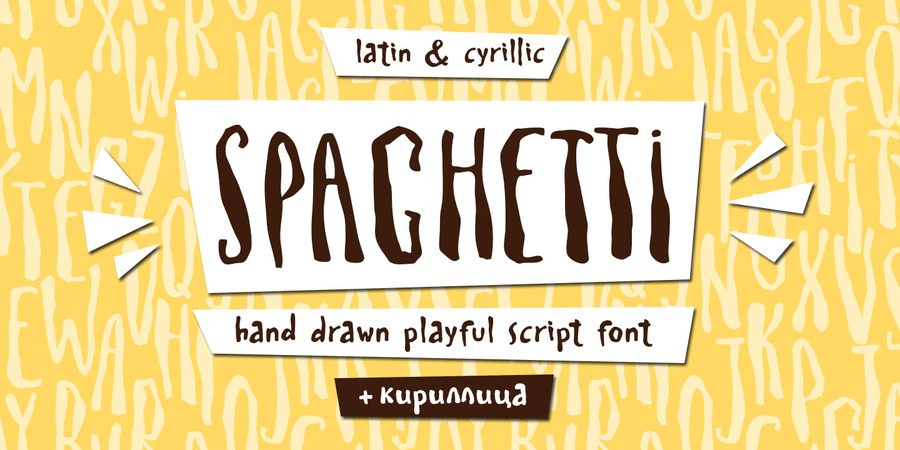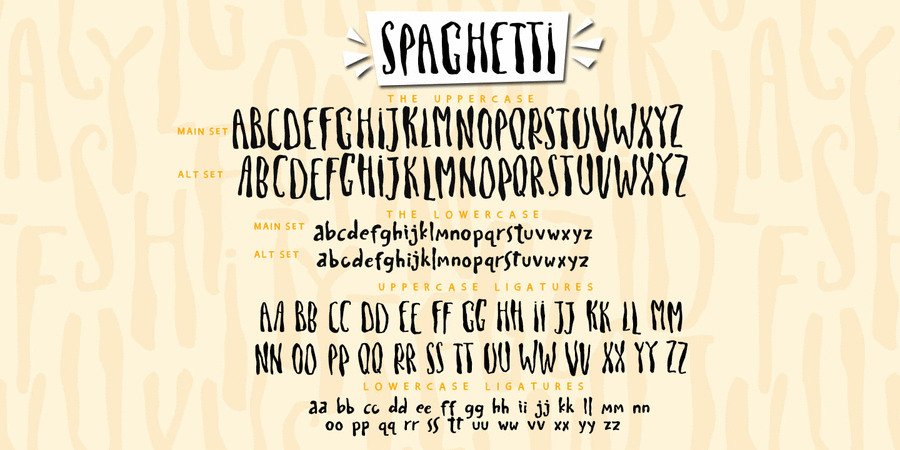
Грайливий симпатичний шрифт Spaghetti включає в себе основний і альтернативний набір великих букв, основний і альтернативний набір малих букв, а також повний набір подвійних букв у верхньому і нижньому регістрі, а також великий діапазон цифр і розділових знаків. Шрифт Spaghetti ідеально підходить для використання у всіх ваших кумедних дизайнерських проектах, будь то логотипи, етикетки, дизайн упаковки, заголовки блогів. Крім того, він буде мати гарний вигляд на листівках, заголовках дитячих книг та інших друкарських проектах. Spaghetti Symbols – це додатковий шрифт з 52 намальованими від руки картинками, цельнімі словами, стрілками і розчерками, який допоможе зробити ваш дизайн більш оригінальним. Комбінуйте елементи та ілюстрації, щоб створювати свої власні дизайни, рамки, роздільники, логотипи та багато іншого (просто за допомогою клавіш A-Z і a-z в доданому шрифті Spaghetti Symbols). Кожному стандартному символу верхнього або нижнього регістру призначається інший символ, тому вам не потрібно графічне програмне забезпечення, просто введіть потрібну літеру. Включена велика мовна підтримка: Мови Західної Європи, Центральної і Південно-Східної Європи, а також кирилиця. ОСОБЛИВОСТІ ШРИФТУ: контекстні альтернативи для більш природного рукописного тексту в програмах з можливістю Opentype, 52 лігатури з подвійних букв для більш індивідуального вигляду, додаткові стилістичні альтернативи для всіх символів. Кодування PUA: доступ до додаткових гліфів можна отримати через карту символів або книгу шрифтів (можна копіювати і вставляти потрібні гліфи, коли панелі Opentype недоступні). Шрифт розробила Ірина Двілюк у 2018 році, а в 2021 додала кирилицю.
журнал, афіша, плакат, обкладинка, листівка, етикетка, комікс, стінгазета, відео, пакування, реклама, анімація, мультфільм, стікер, наліпка, привітання, меню Адаптованість гарнітури до носіїв:
Асоціації з сімейством шрифтів SPAGHETTIОсобистість і характер гарнітури:
зловісний, злий, цвинтарний, страшний, заразний, мертвий, фрік, дивний, божевільний, химерний, окультний, таємничий, загадковий, експериментальний, моторошний, кріповий, екзотичний, вернакулярний, макабричний, психоделічний, навіжений, смішний, наївний, рукотворний, грайливий, потішний, прикольний, характерний, крафтовий, кустарний, саморобний, органічний, артізанальний, шорсткий, дикий, перчений, неформальний, легковажний, неохайний, звіриний, карикатурний, мультяшний, недбалий, домашній, ручний, осінній, високий, оригінальний, живий, дитячий, лісовий, нервовий, запальний, емоційний, яскравий, веселий, радісний, літній, кольоровий, інфантильний, доброзичливий, добрий, щасливий, смачний, динамічний, помітний, милий, зелений, пластичний, святковий, творчий
хоррор, фільм жахів, іграшка, гра, анімація, розваги, геловін, атракціон, вірус, хвороба, кладовище, закляття, магія, прокляття, мультфільм, Аддамс, мрець, привид, жуки, павуки, комахи, монстр, чудовисько, відьма, зомбі, Самайн, квест, джокер, зоомагазин, тварини, дитяча книжка, канікули, соус, кетчуп, чіпси, закуска, їжа, спеції, перець, кафе, хенд мейд, фаст фуд, піцца, графіка, ілюстрація, дім, свято, вечірка, реклама, відпочинок, фарби, дача, табір, фестиваль, ярмарок, базар, школа, гумор, Хюґе, ранок Гарнітура має ознаки стилів: